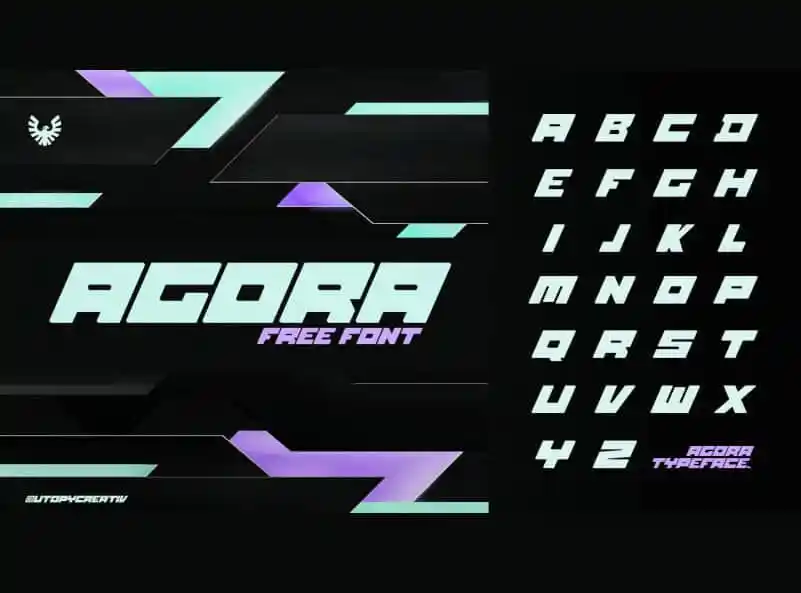
Agora Free Font – Fonte Grátis
Agora Free Font
Agora Free Font é uma elegante fonte robusta e quadrada disponível gratuitamente para uso pessoal apenas. Através deste projeto, Utopy não apenas proporciona acesso a uma fonte versátil e minimalista, mas também incentiva os usuários a considerar doações ou entrar em contato caso se sintam confortáveis com isso. Perfeita para ambientes retro e contemporâneos, esta fonte é ideal para personalizar seus projetos digitais de forma única. Se você está procurando por uma fonte clássica e moderna ao mesmo tempo, Agora Free Font provavelmente será sua escolha perfeita.
Designer: Utopy